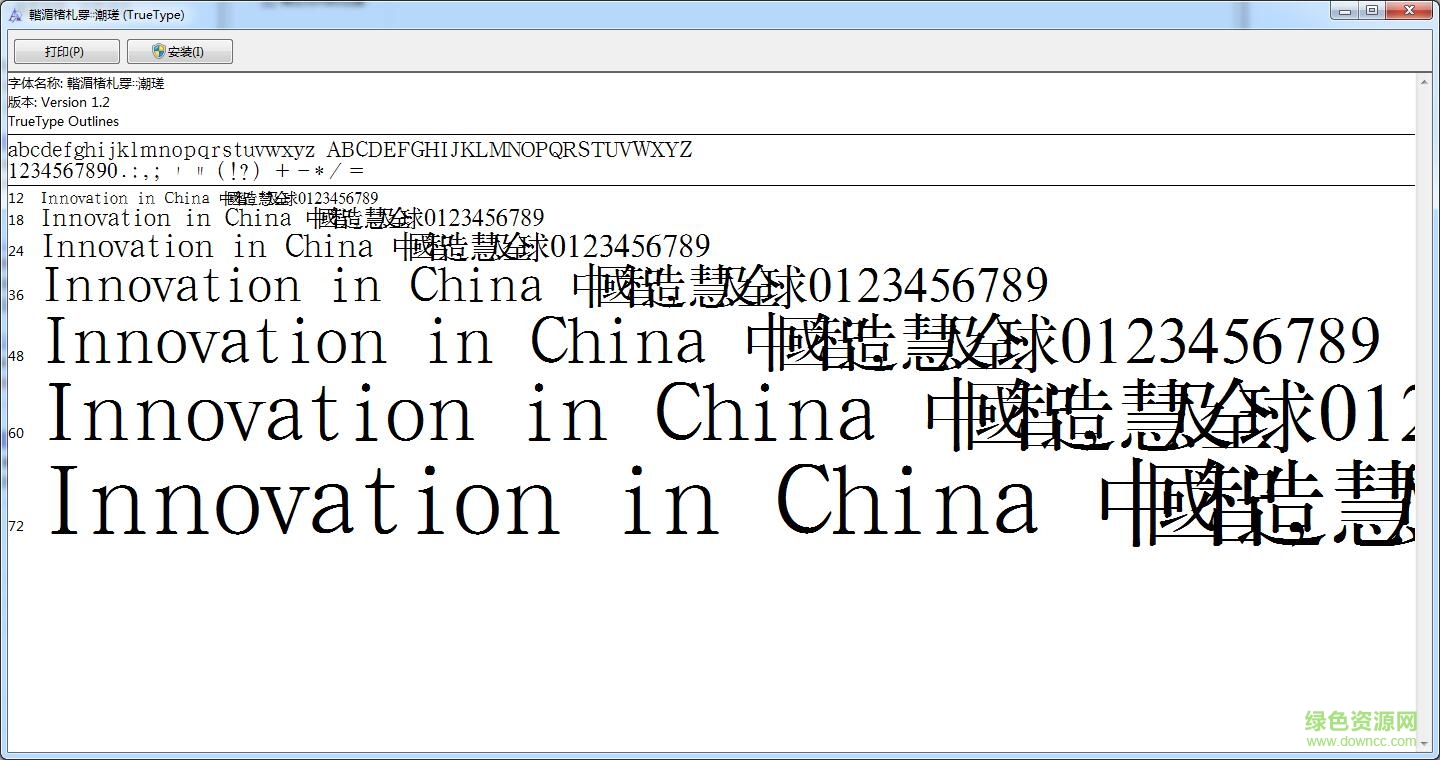
漢鼎繁標(biāo)宋字體是一款免費(fèi)的字體,這款字體屬于漢鼎字體系列繁體應(yīng)用!可以用來(lái)設(shè)計(jì)廣告標(biāo)題、平面設(shè)計(jì)等,讓你的設(shè)計(jì)平面中的字體也更加引人注目,非常的實(shí)用,需要的朋友可別錯(cuò)過(guò)了,大家可以來(lái)綠色資源網(wǎng)免費(fèi)下載使用!
字體效果比較正規(guī);
字體使用范圍廣。